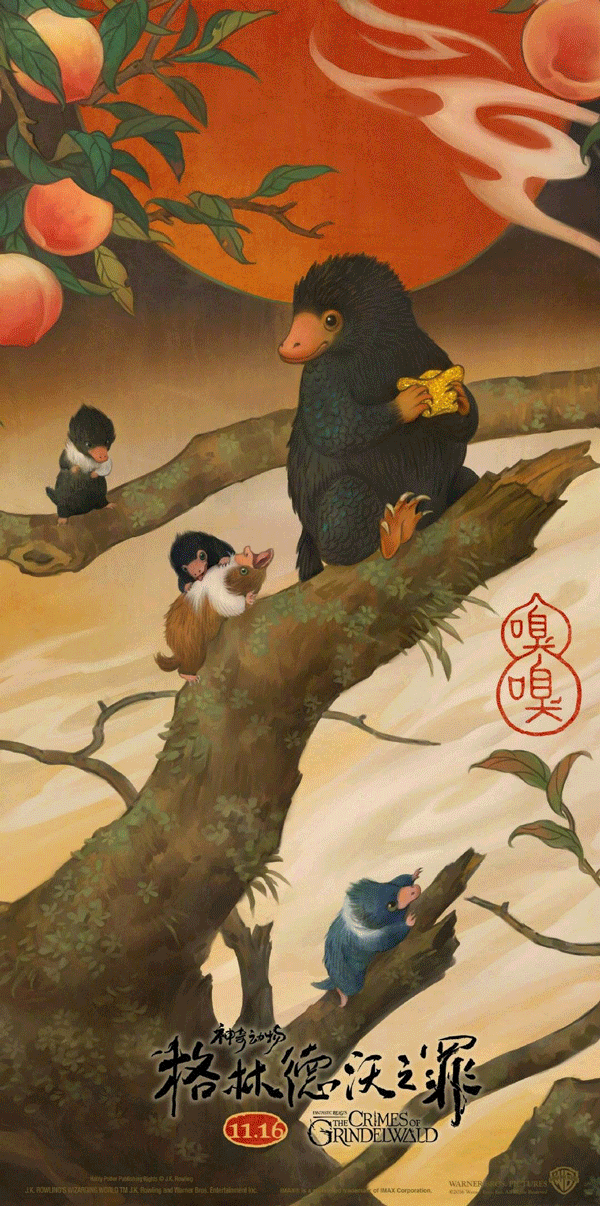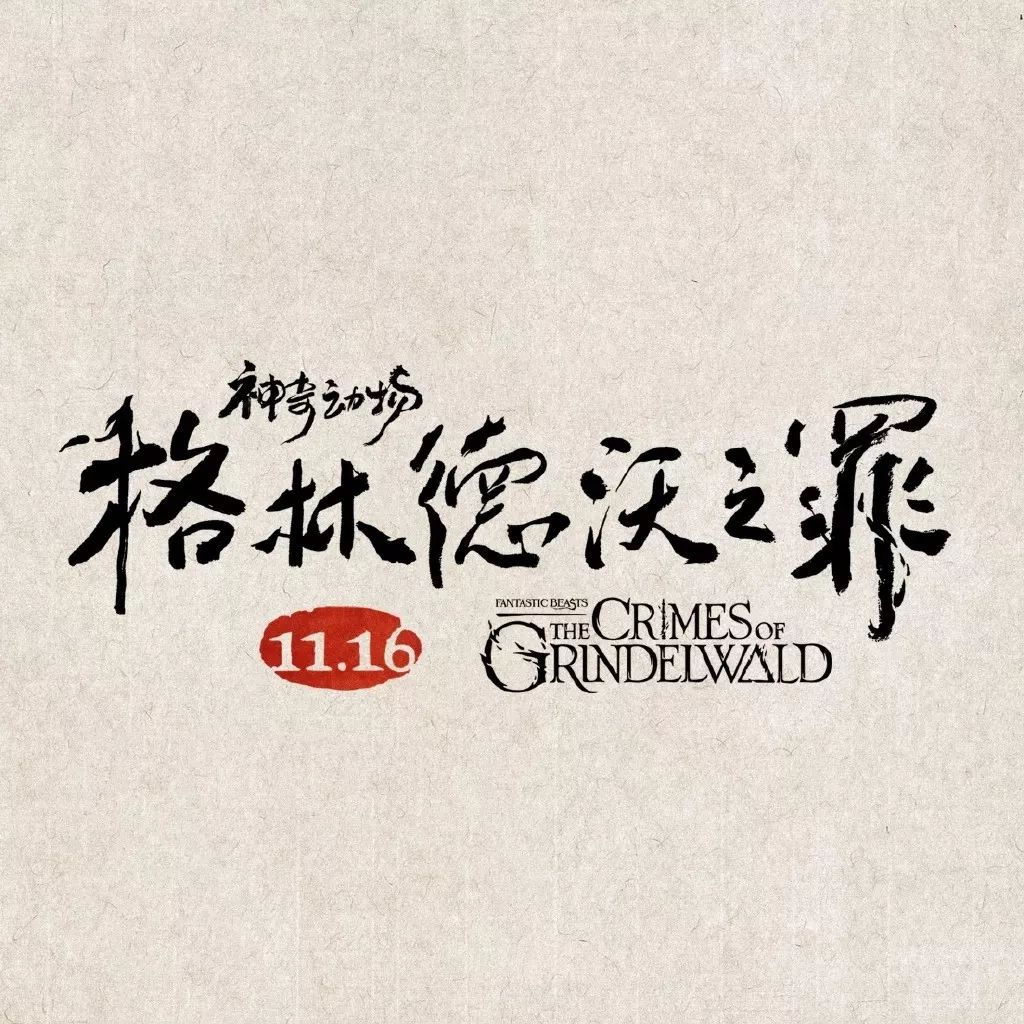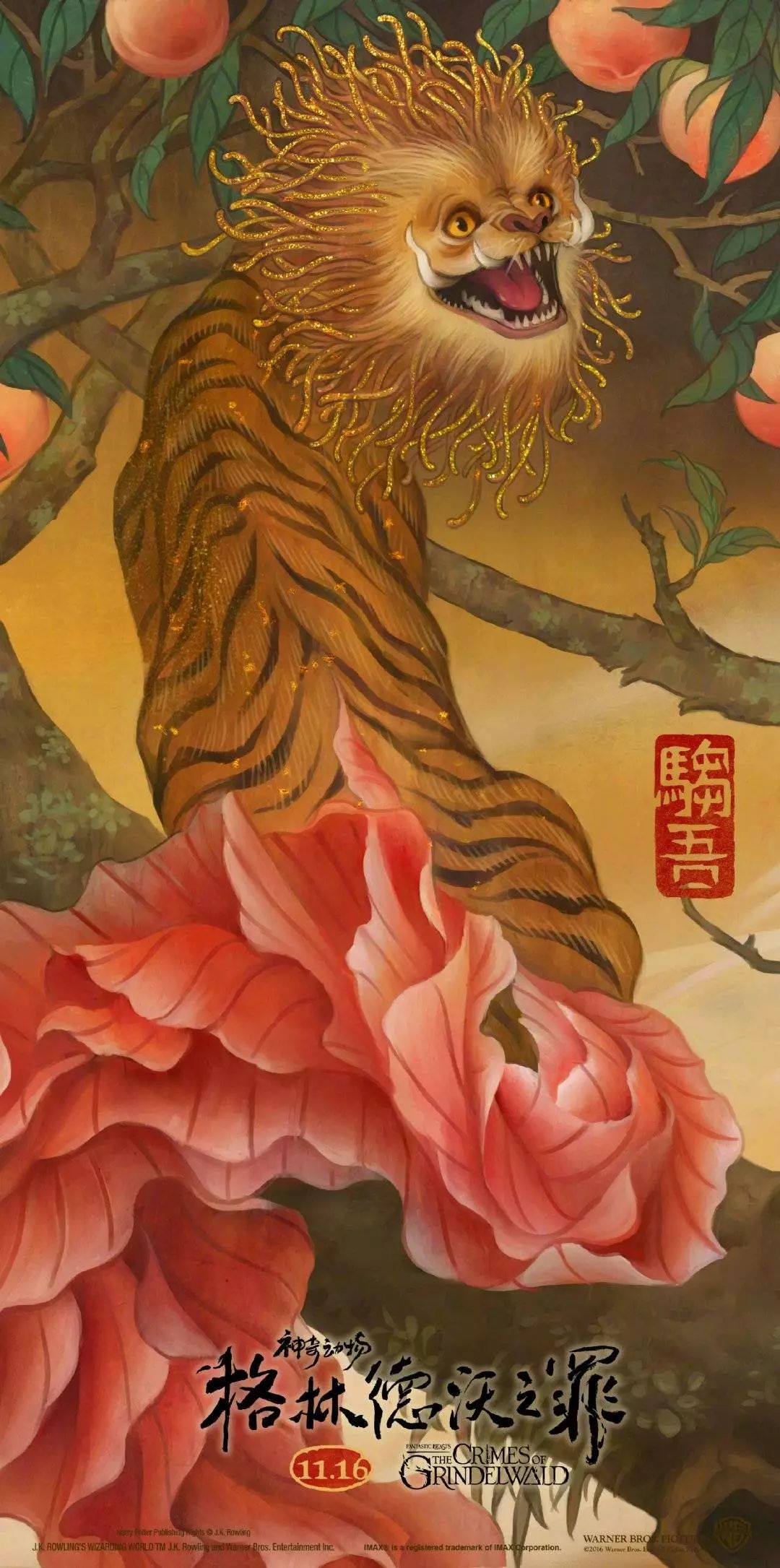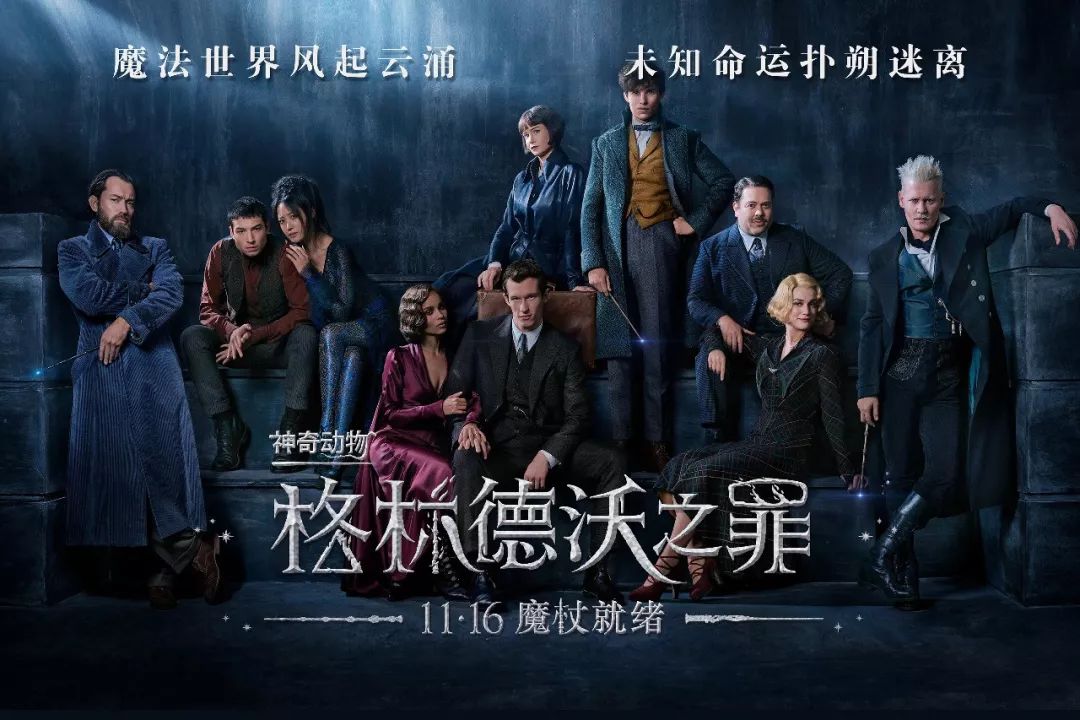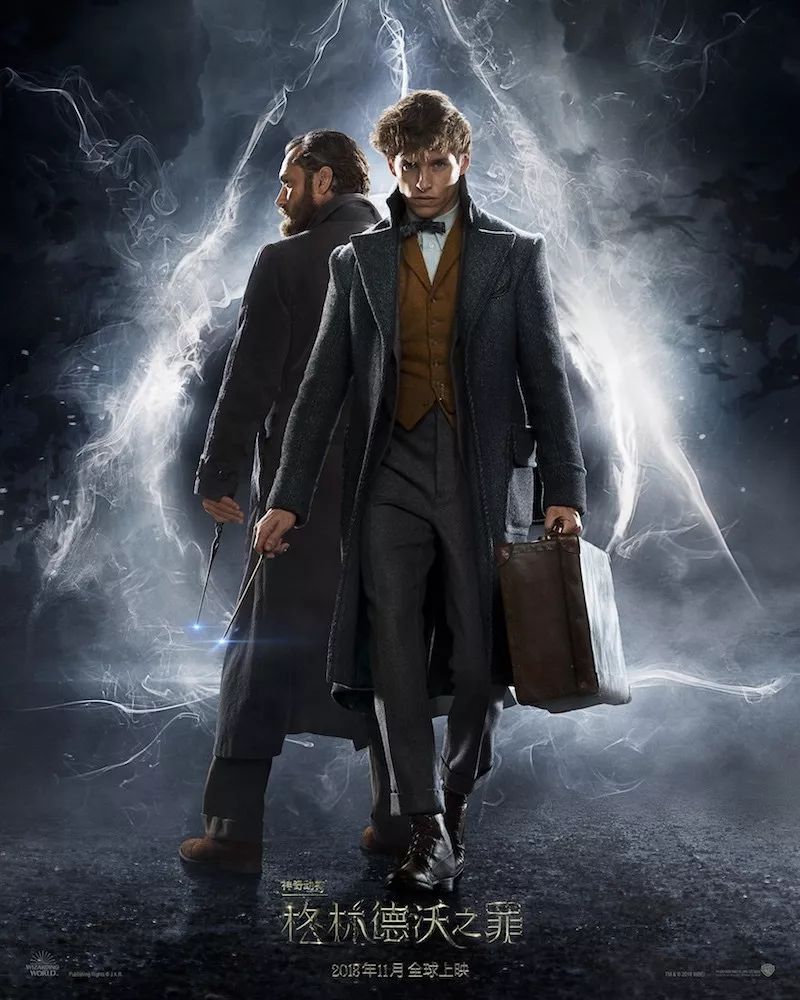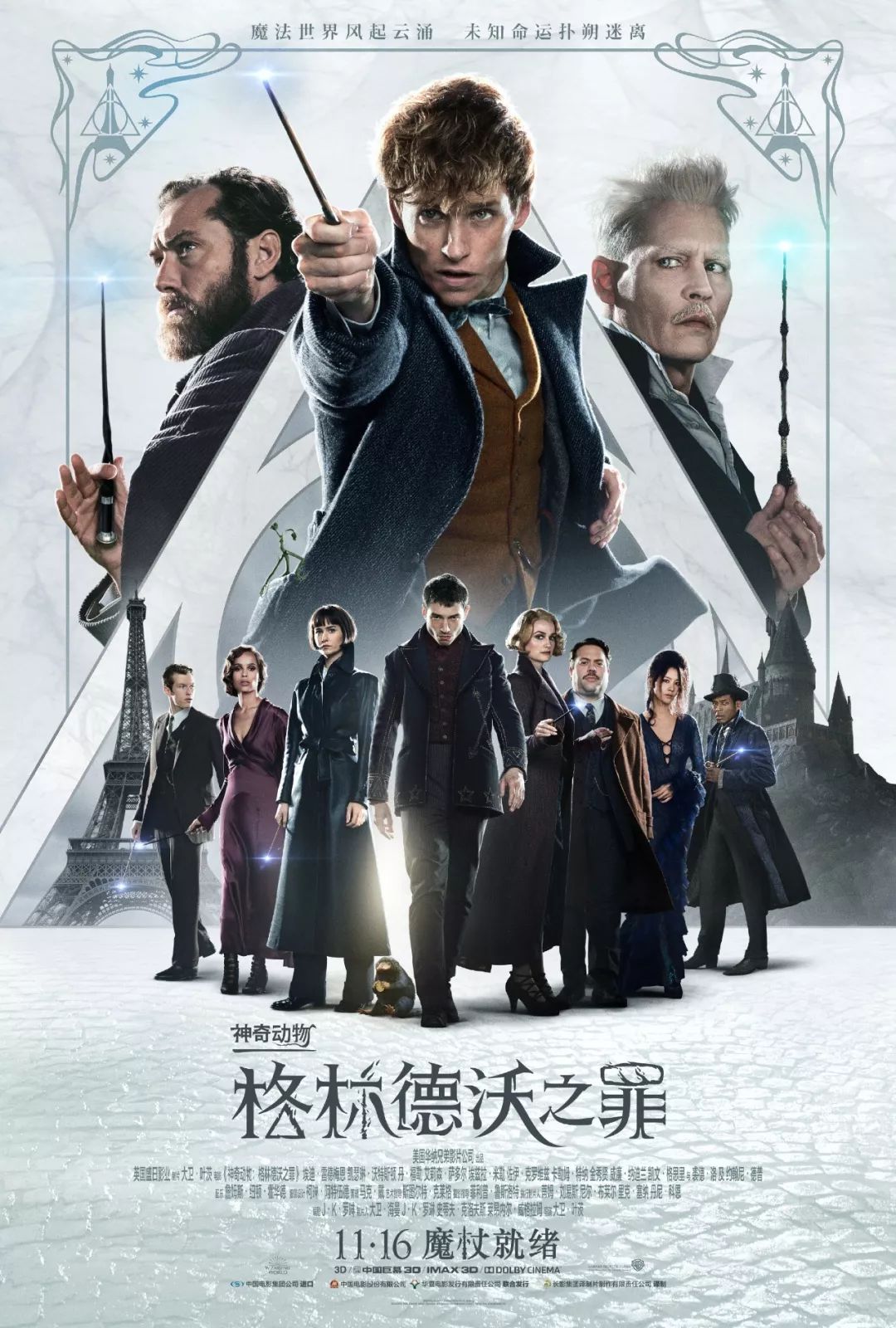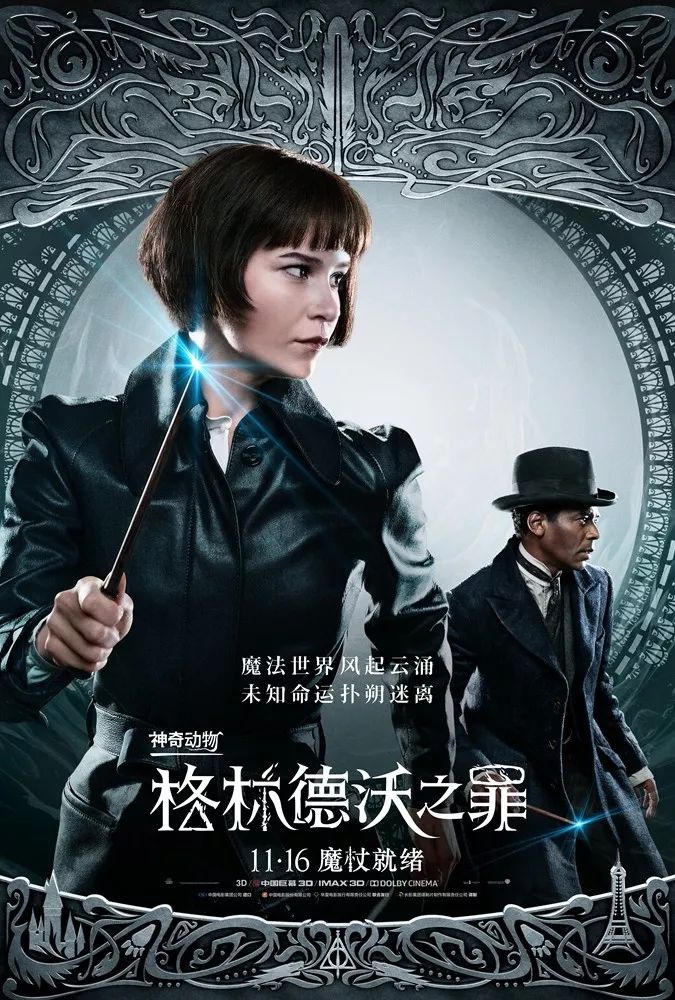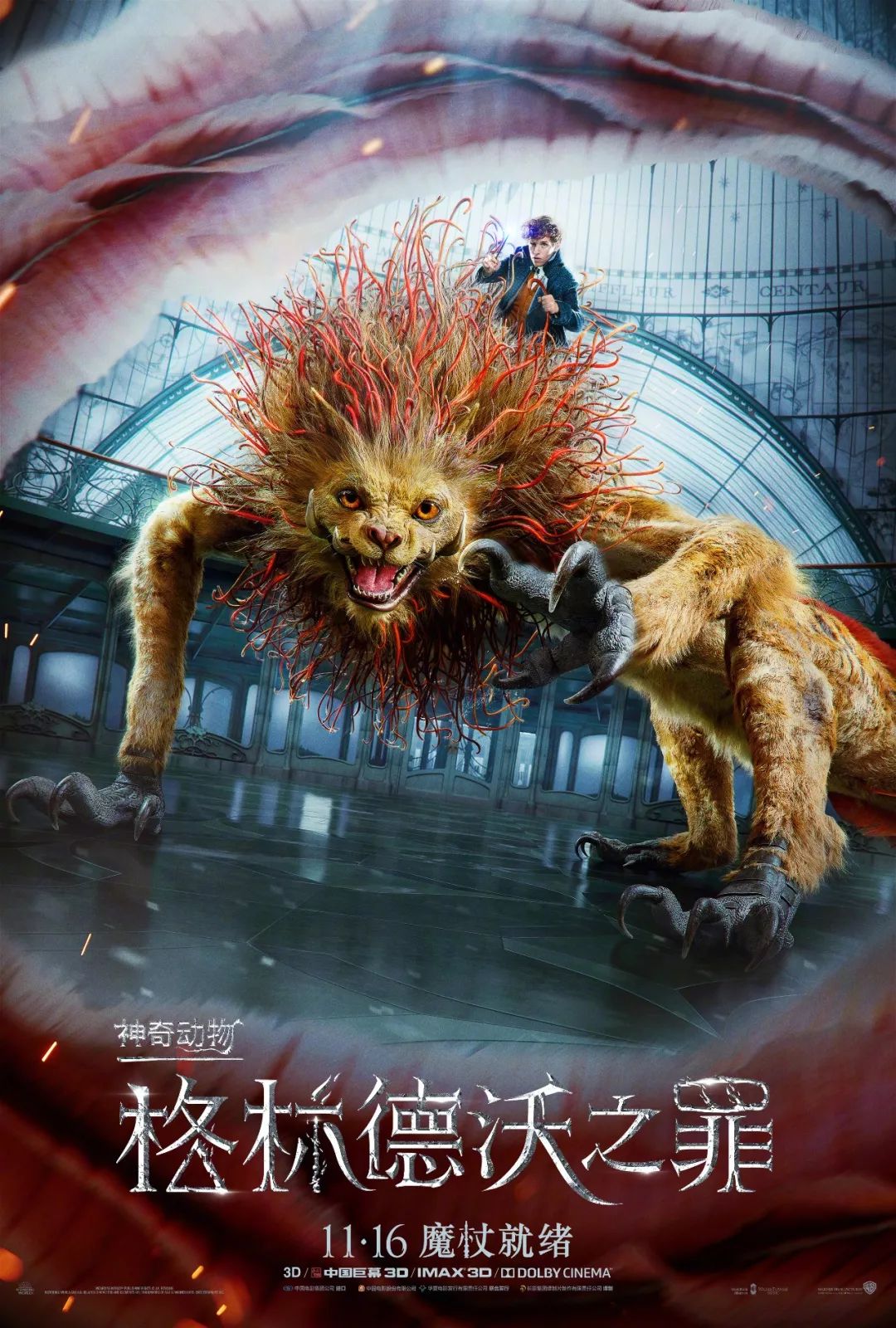
《神奇动物2》的这些细节,你真的看懂了吗?
周末柚子去看了《神奇动物:格林德沃之罪》,作为一个没怎么看全过哈利波特系列,更没看过神奇动物第一部的麻瓜,朋友提醒过我,你可能会睡觉,或者根本不懂里面的梗~
不过我还是鼓起勇气去看了,虽然它确实对普通观众不太友好,人物太多,支线太散.……
但里面的特效还是挺燃的,特别是看到了我心心念念的驺吾~
这很山海经
驺吾出自《山海经·海内北经》:“ 林氏国 ,有珍兽,大若虎,五采毕具,尾长于身,名曰驺吾,乘之日行千里。”
我百度搜的时候是这个样子,额,跟想象中的差距有点大~
可在中国艺术家张春(大鱼海棠导演)的操刀下,就完全不一样了,金光闪闪的毛皮、色彩斑斓长尾巴,再加上尖獠牙,可谓非常华丽耀眼了。
LOGO也以毛笔字形式重新演绎,笔画极具动感和韵律,隐隐有种“会从海报中跳出来”的感觉。
还有其它五个神兽,只爱钱的锦鲤嗅嗅、会开锁的护树罗锅、新出现的马形水怪、哈利波特里的卜鸟、邪恶反派的玛达戈猫。它们的名字均是以落款印章的形式呈现,搭配传统色调,十分中国风。
说到这,让人不免想起第一部,当时也是由张春创作,走的是团扇风格。
但这次采用了不一样的概念,六幅神兽既彼此独立,又完整统一,拼起来是一幅十分惊艳的长卷屏风,有的在桃树上,有的在水里,寓意“六幅海报得神兽”,谐音中国的“福禄寿”(为了抢中国观众兜里的银子,也是煞费苦心了)。
这很哈利波特
看电影预告片的时候,不知道你们有没有发现这个罗氏宇宙(J.K. Rowling’s Wizarding World)的秘密~
没错,我们的男主角纽扣,啊不,纽特的筷子,哦不,魔杖,就是从左到右第六根了。
还有蒂娜、奎妮、格林德沃,罗琳这是憋了个大招,要建立宇宙,召唤神龙啊!不过也有网友说了,哈利波特系列,可以靠我们这代人的情怀捞一个世纪的钱,哈哈!
不过细细比较,《神奇动物2》的海报字体跟哈利波特不太一样,闪着略低调的金属光芒 ,跟罗氏宇宙的字体很像,且暗藏玄机,“▲”代表了隐形斗篷,“丨”代表了老魔杖,“O”代表了复活石,分别代表了三件死亡圣器。
比第一部用心多了,不管是中文,还是英文,都只在“物”、“s”上做了一下兽性的延展,要不是做了场景的特效弥补,看起来会略敷衍。
这很格林德沃
整体大小不一,采用宋体风格,横细竖粗,起落有衬线,重心略偏高,基本每个字都有一个关键性造型,比如“格”字的“口”变为“▲”,“林”字的“丨”变为魔杖,另外,笔触末端的亮光、枝丫造型也很有魔幻感。
确实动物也没第一部多了,除了驺吾出场三次,还有嗅嗅不定时出现,其它感觉都是打酱油的,特别是那个“龙形海带”,明明很厉害,却只被骑了一次,耍了次帅,就没了~
好在驺吾的反差萌,让人惊喜不已,虽然一声怒吼吓得路人四处逃散,但一只逗猫棒就被纽特轻松制服,呆萌得像一只大喵~
所以第一张海报当然要给它了,老霸气了有木有!
师生版海报,以光影+烟雾的效果,勾勒出背后的神秘符号,看起来有点酷炫!
大型交响乐团海报,每人一个指挥棒,你能看出几个人物排列的“三角形”?
“三角关系”海报,谁让你插足cp组合了,不过这里也有神秘符号,形成视觉上的平衡。
双人海报,将角色一前一后放置,有层次感的同时,交代了人物关系。分布在画面上下方的金属花纹元素,像一只睁开的眼睛,感觉随时有人在窥视你。
最后这个单人写真海报,采用大特写的方式,白色带有繁复花纹的边框,每个人都不一样。当你将头伸出画框,悬念感就出来了。
这很名侦探柯南
从第一部,我就发现小雀斑有点名侦探柯南的影子,还有小领结。
到这一部,更是加入了寻找蛛丝马迹的魔法,真的很穿越。
不过这些插画版海报是不是更似曾相识,哈哈~
看看日本版的海报,是不是更像了,果然艺术无国界啊~